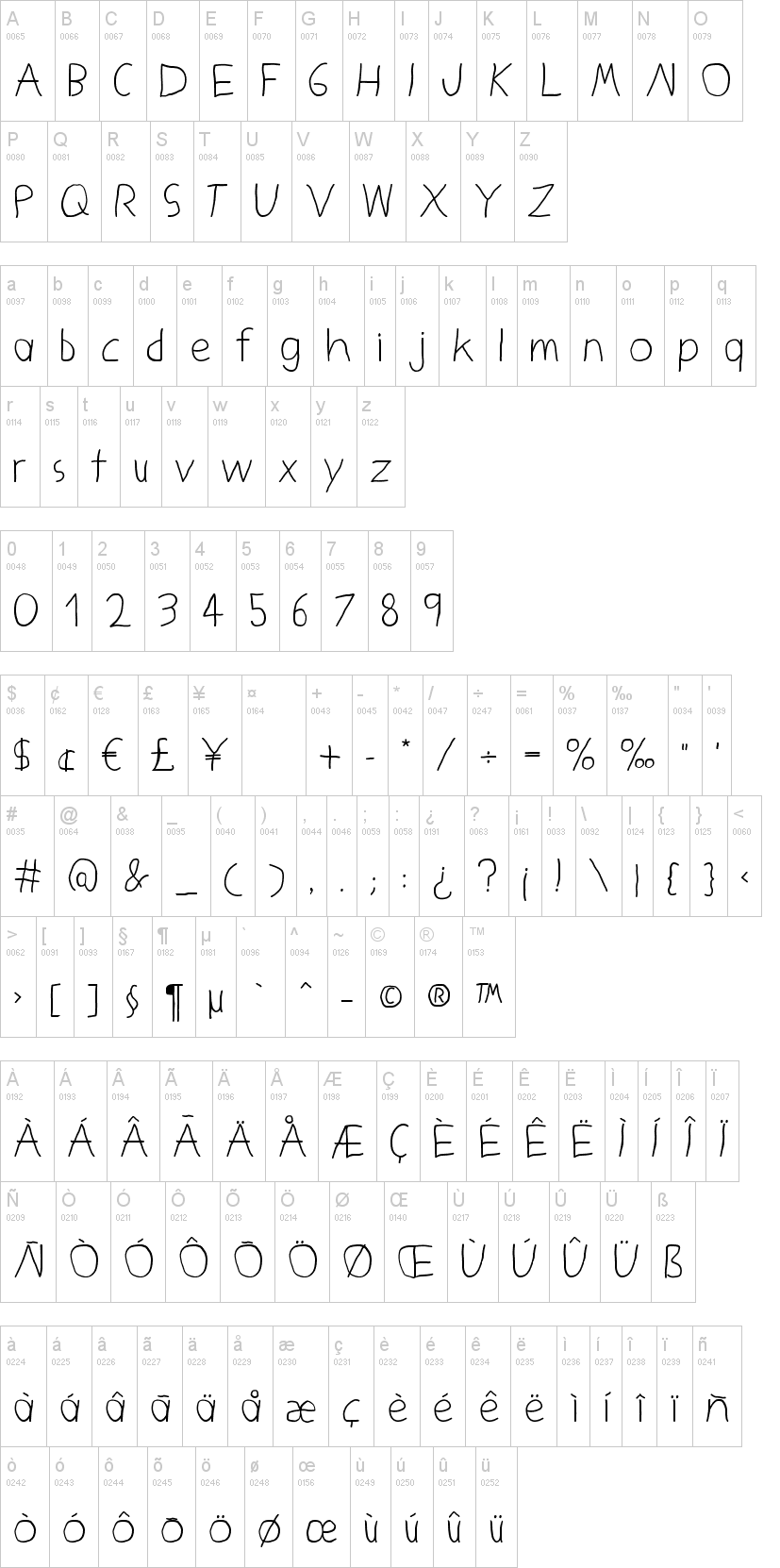
Шрифт Kids Future
Esta tipografía es un proyecto que trabajamos en connjunto con Common Hope, http://www.commonhope.org/or conocida en español como Familias de esperanza.
Common Hope trabaja en Guatemala, un país con uno de los más altos índices de analfabetismo en Latinoamérica. Así que buscando una solución al problema, pensamos en una idea muy simple: Crear y vender una tipografía como una forma de financiar los programas de lectura de Common Hope.
Trabajamos con un grupo de niños de primer grado, que ya están dentro del programa de Common Hope, cada uno de ellos creó un alfabeto. Después de un proceso de selección, retoque y digitalización el resultado fue: Kids Future. Una tipografía hecha a mano, distinta y con espíritu infantil.